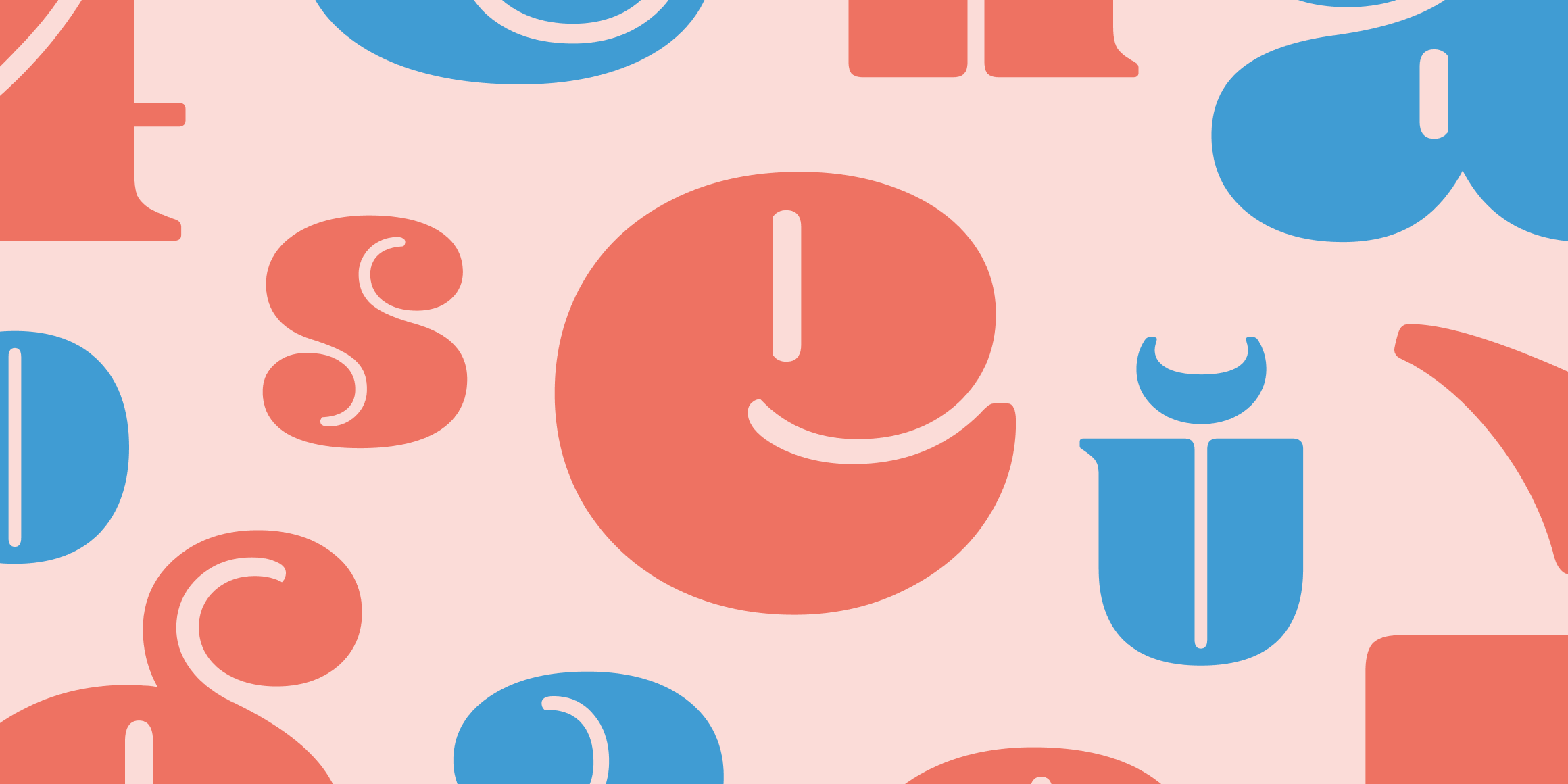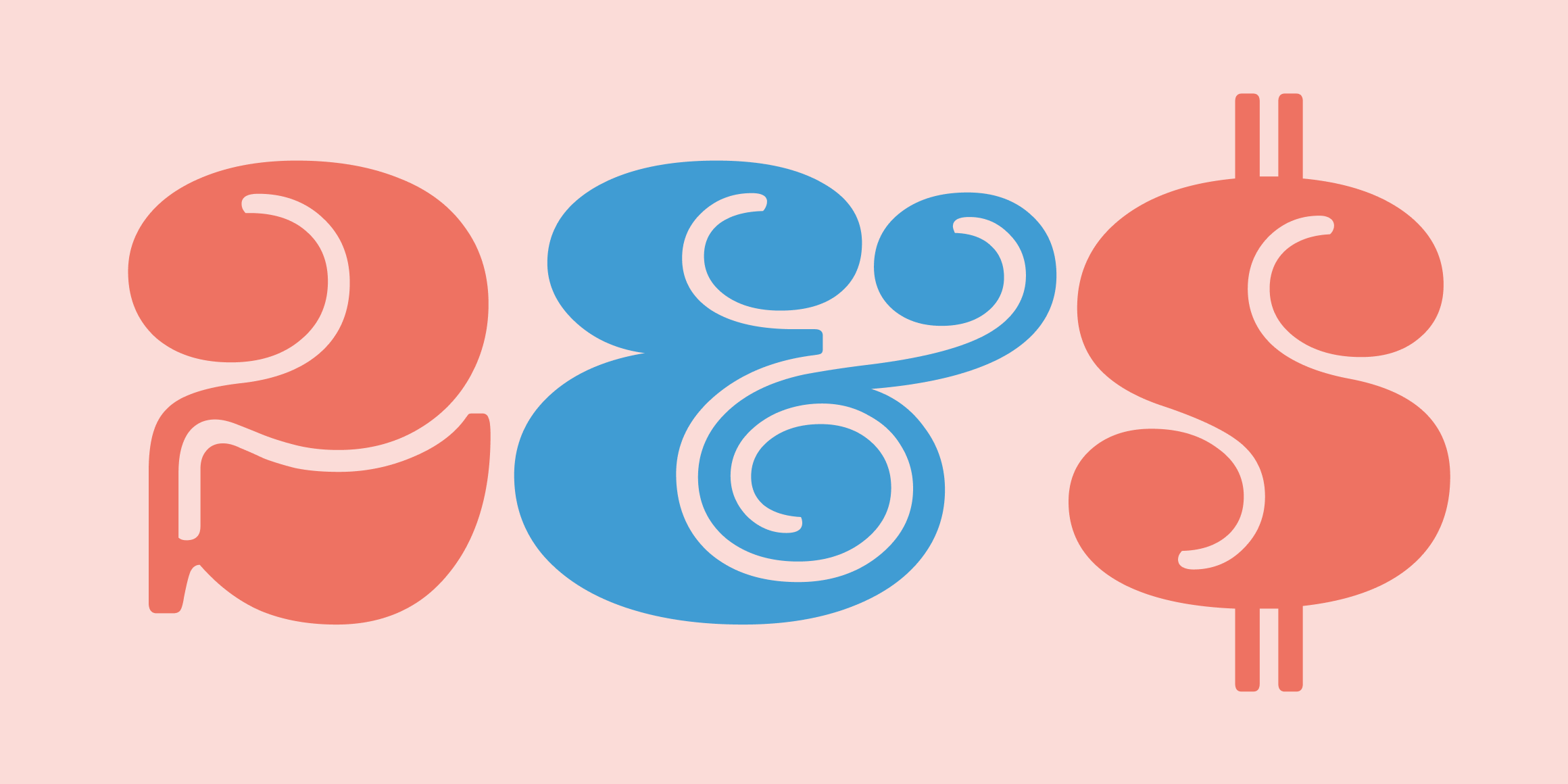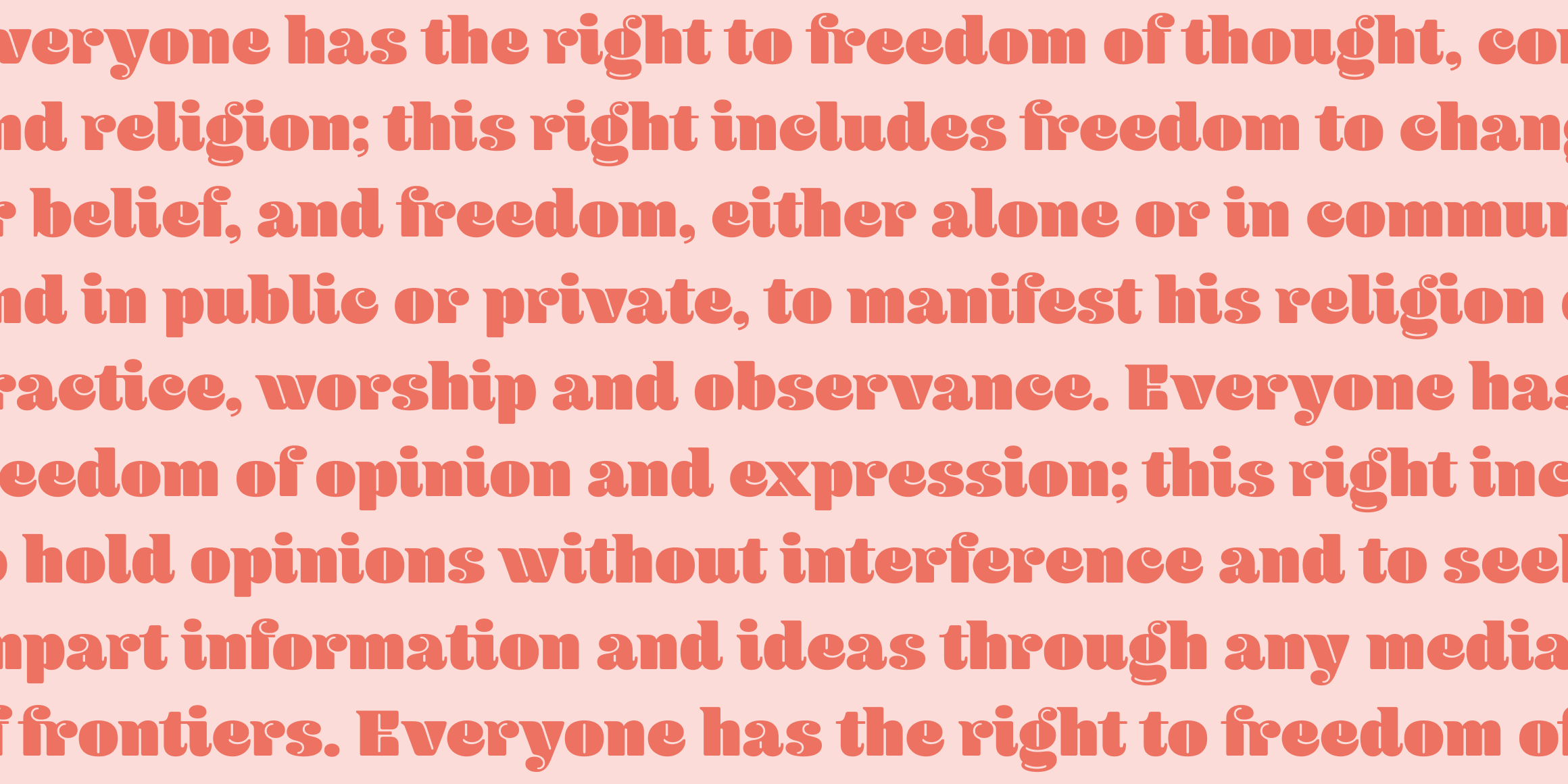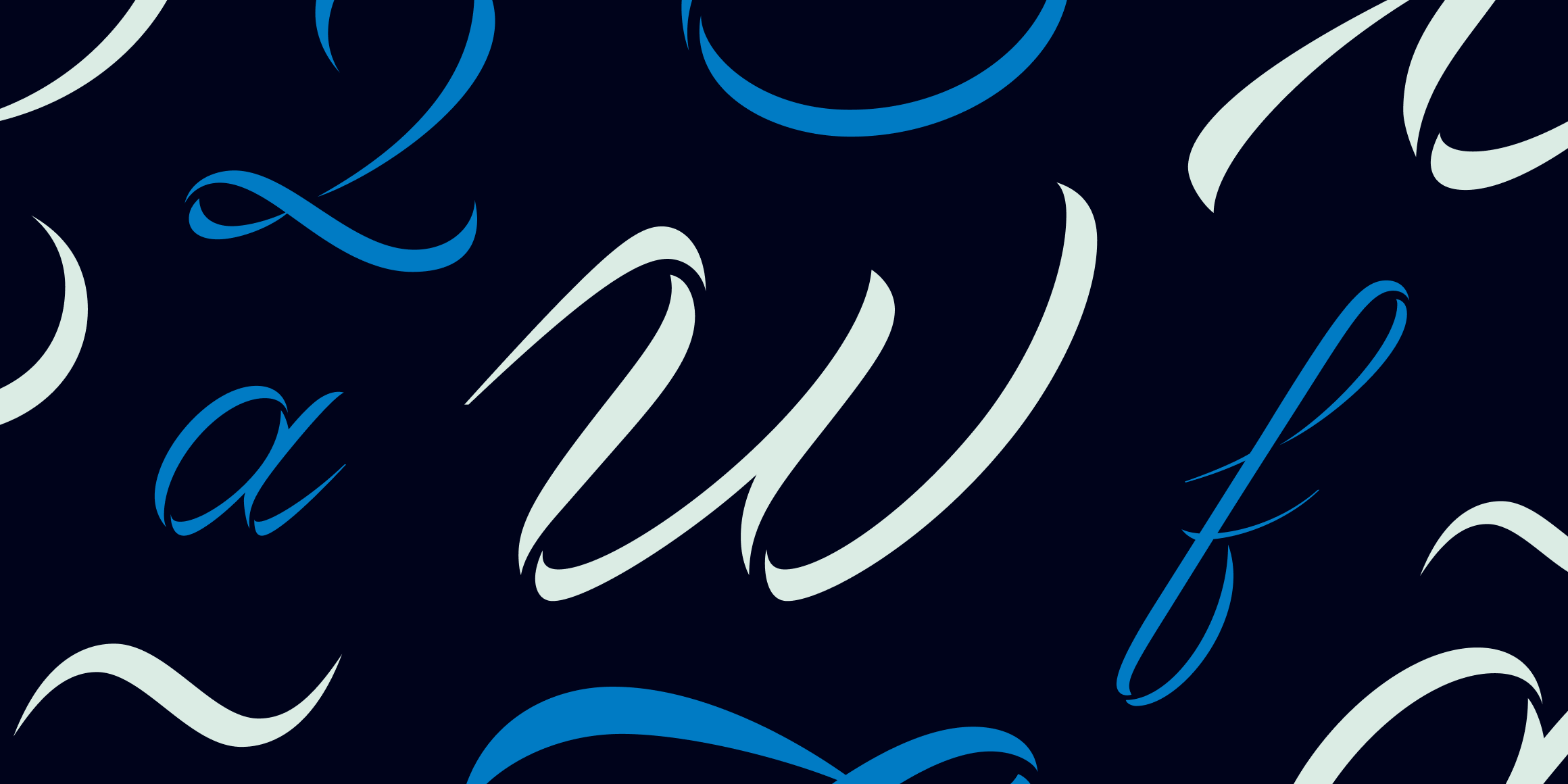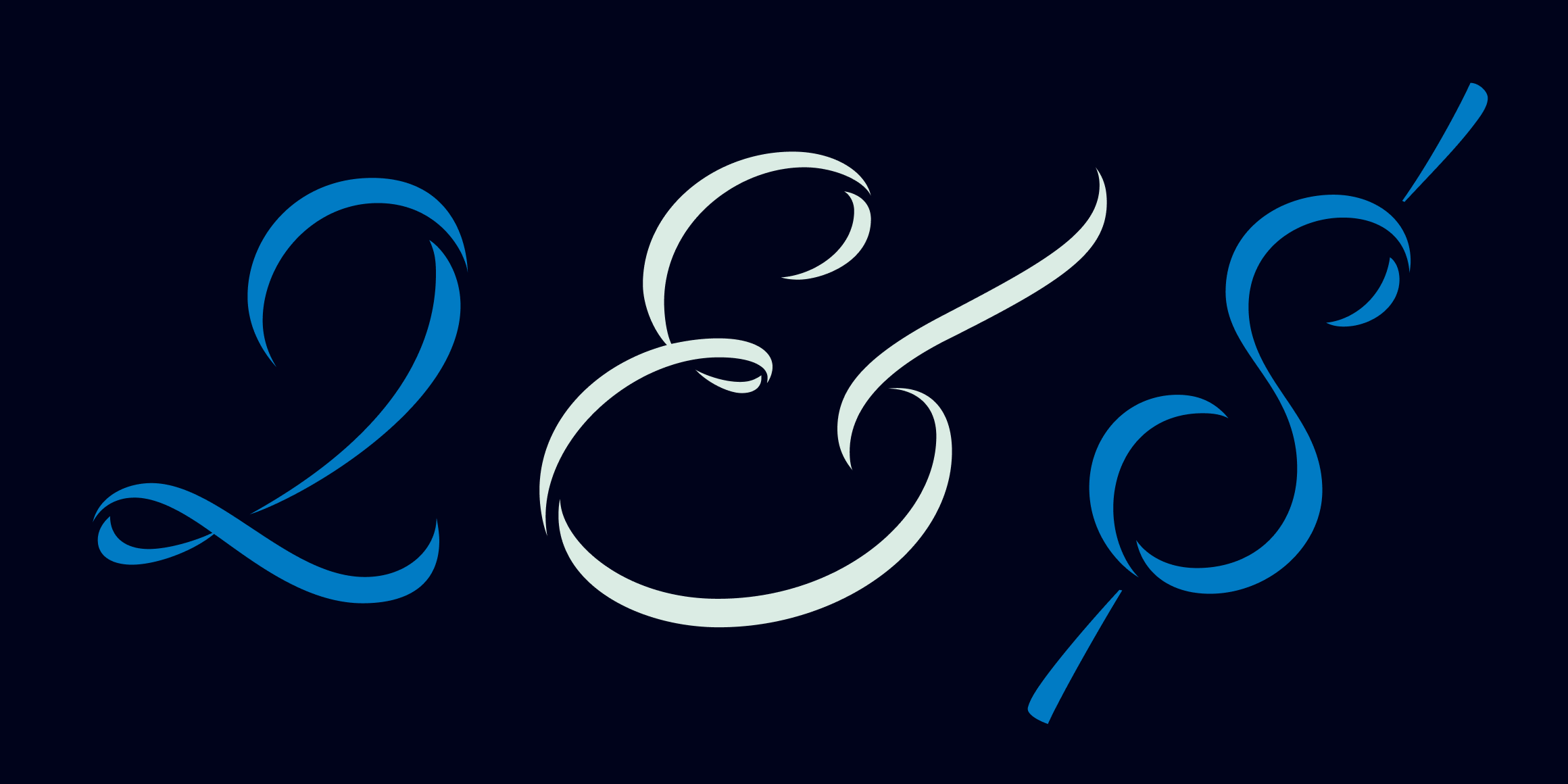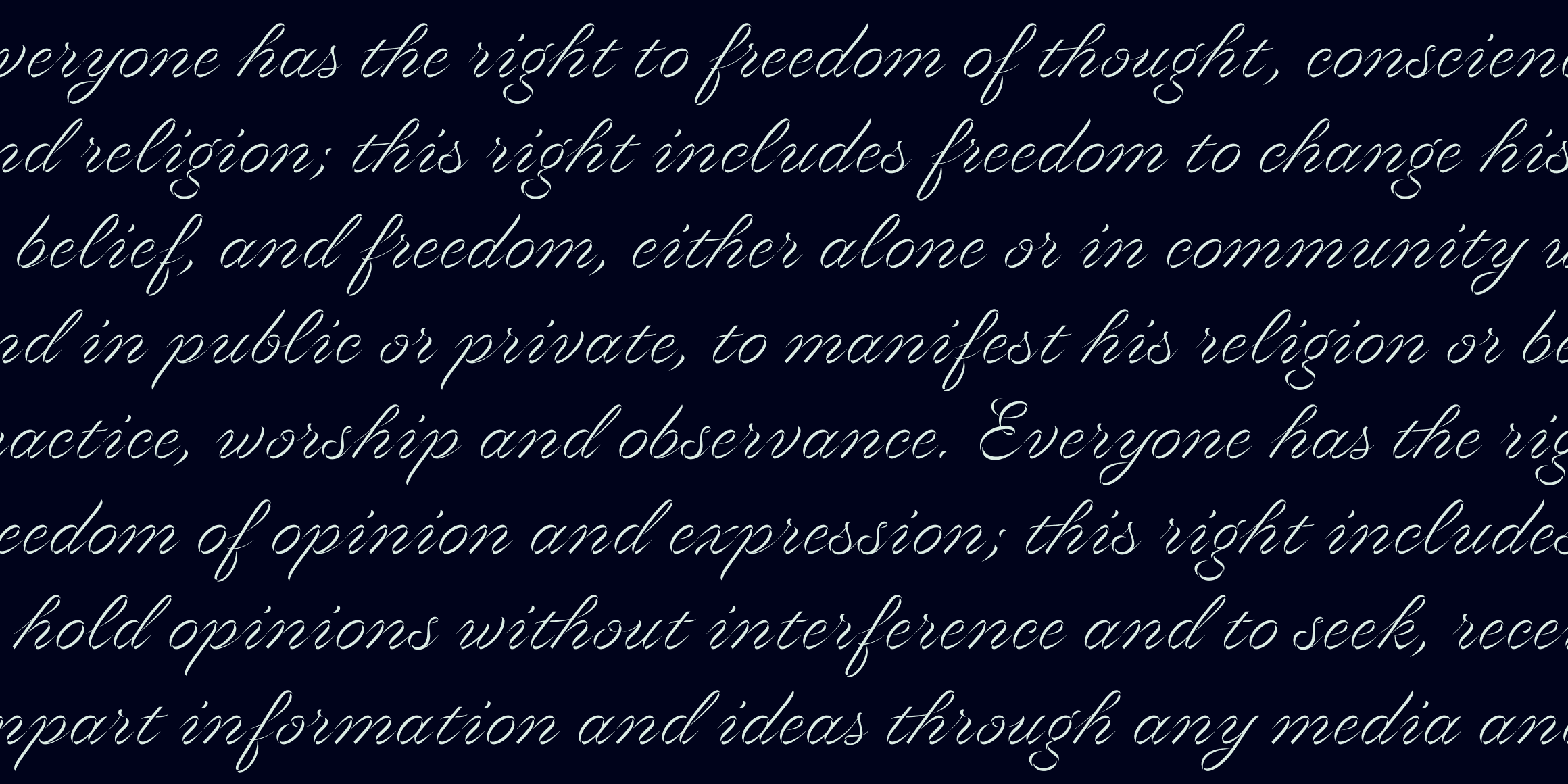
Welcome, 달튼막(Dalton Maag)!
세계적인 명성을 가지고 있는 타입 스튜디오 달튼막(Dalton Maag)이 산돌구름에 입점했습니다.
넷플릭스 UI와 자막에 전반적으로 사용되고 있는 「Netflix Sans」,
그리고 최근 새로 공개된 대한항공의 전용서체 「Korean Air Sans」 까지!
이런 엄청난 전용서체들을 만든 글로벌 타입 디자인 스튜디오랍니다.
「Netflix Sans」 가 사용된 넷플릭스 로그인 페이지
대한항공 전용서체 「Korean Air Sans」
이런 전용서체는 해당 브랜드만을 위한 것이기에 아쉽게도 직접 써볼 수는 없지만,
이 서체들을 만든 디자이너들이 똑같은 정성을 담아 높은 완성도로 제작한 상업용 폰트 라이브러리가 있다는 사실!
산돌구름 에디터 Pick!
달튼막의 대표 폰트 패밀리인 「Aktiv Grotesk」은 네오-그로테스크 장르의 깔끔한 산세리프 폰트인데요.
브랜딩, 편집, UI 어디에든 유용하게 활용할 수 있어, 사용성을 중요시하는 달튼막의 정체성을 톡톡히 느끼실 수 있을 거에요.
또 주목할 만한 폰트로는 은은한 표정이 느껴지는 「Effra」, 지오메트릭하고 깔끔한 인상의 「Objectiv」,
귀엽고 통통한 느낌의 「Blenny」, 화려하고 정교한 스크립트 「Volina」,
그리고 엄청난 대가족 구성의 우아한 세리프 「Marble Arch」 이렇게 추천드릴게요.